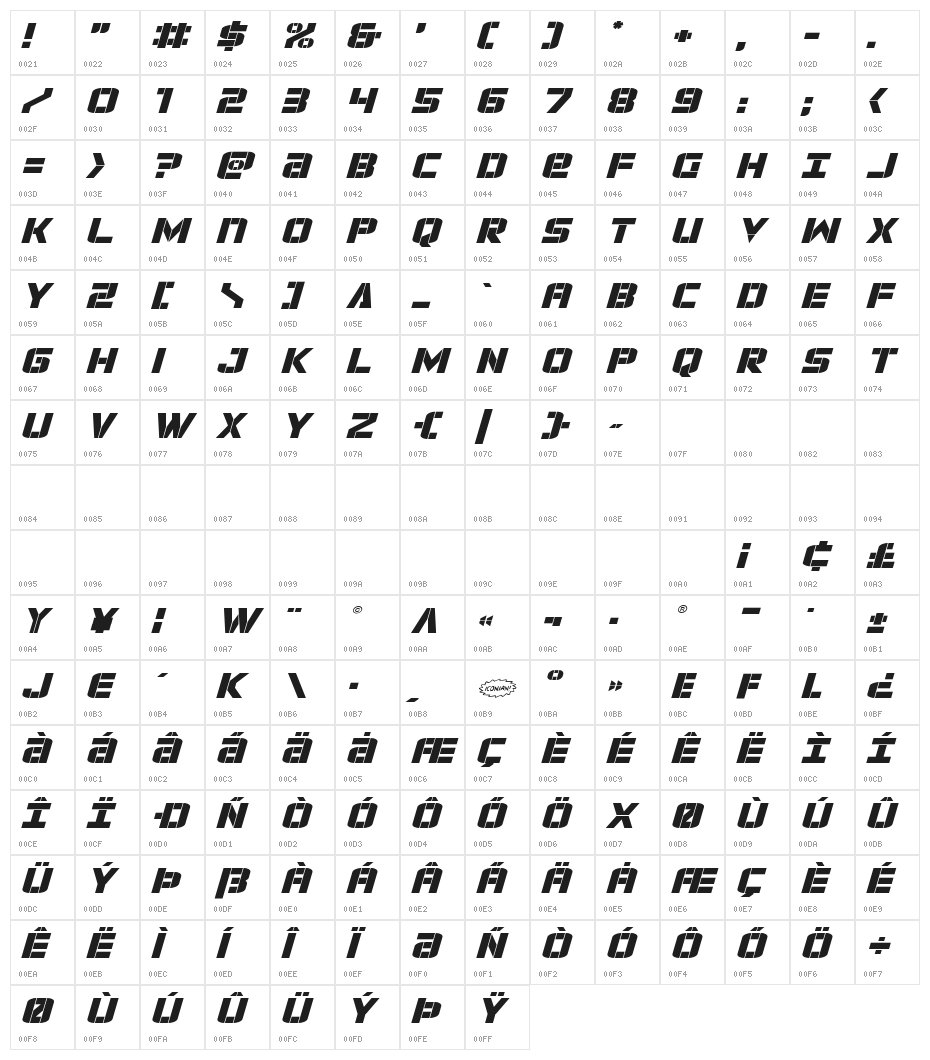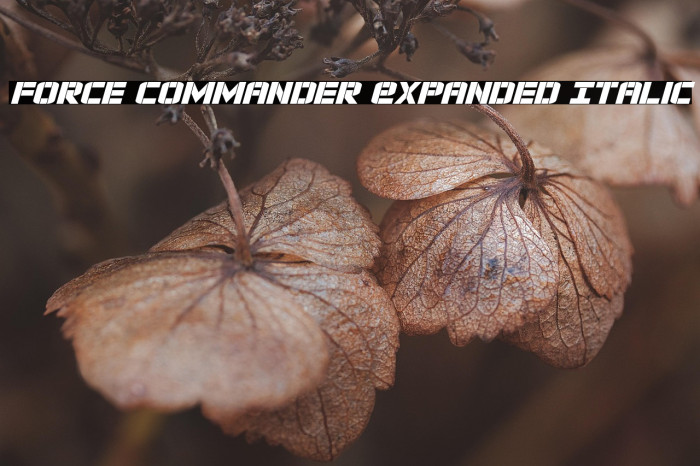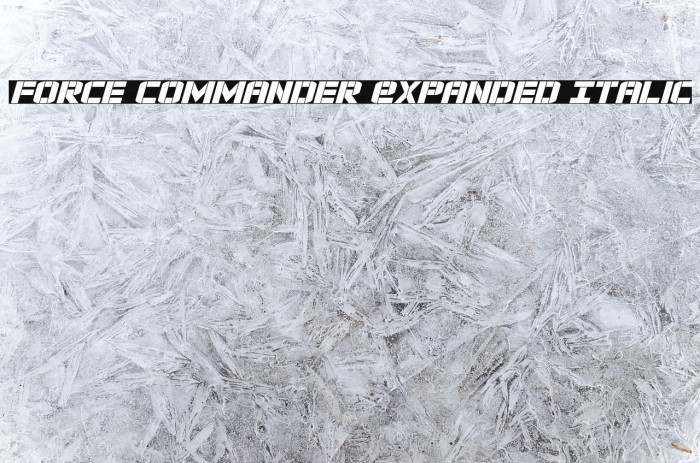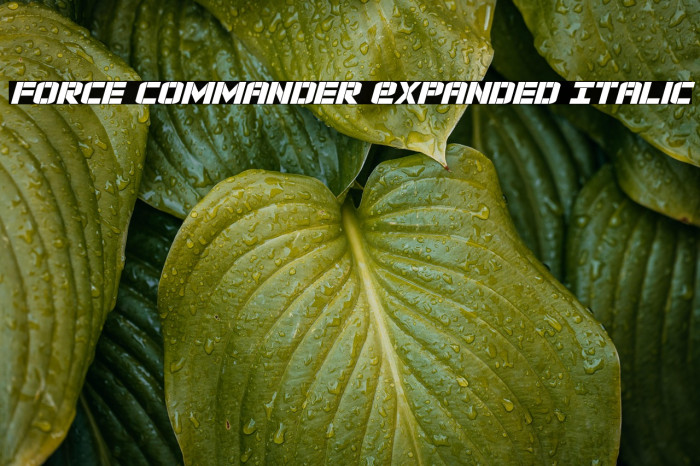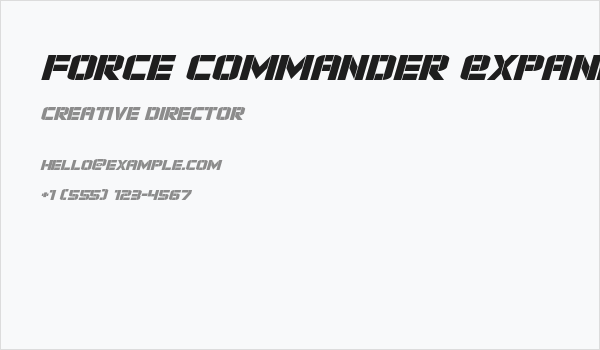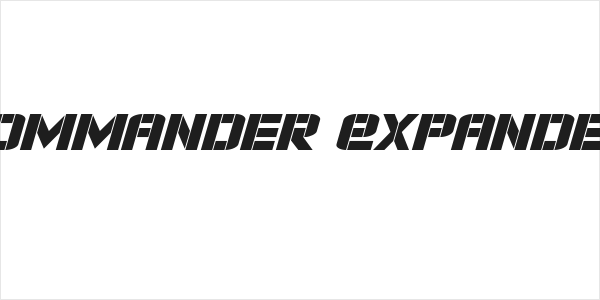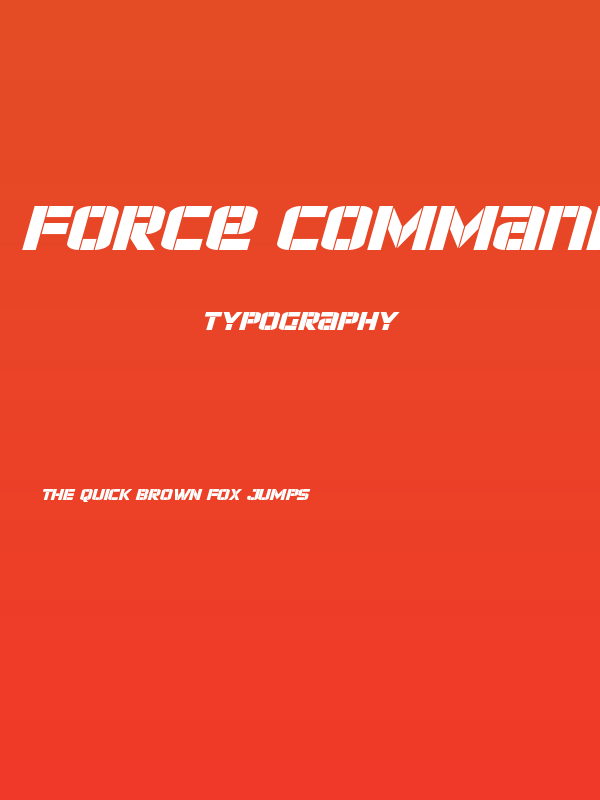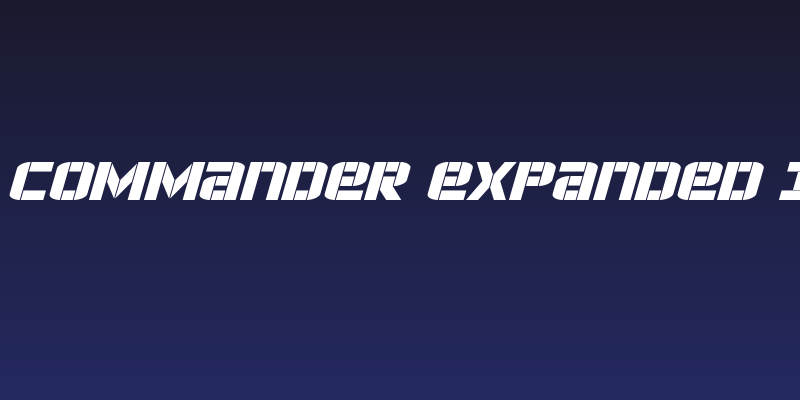
Force Commander Expanded Italic Font
✎ Futuristic
| Vorgeschlagene Projekte | Ideal for use in technology branding, sports team logos, video game titles, and sci-fi themed posters. |